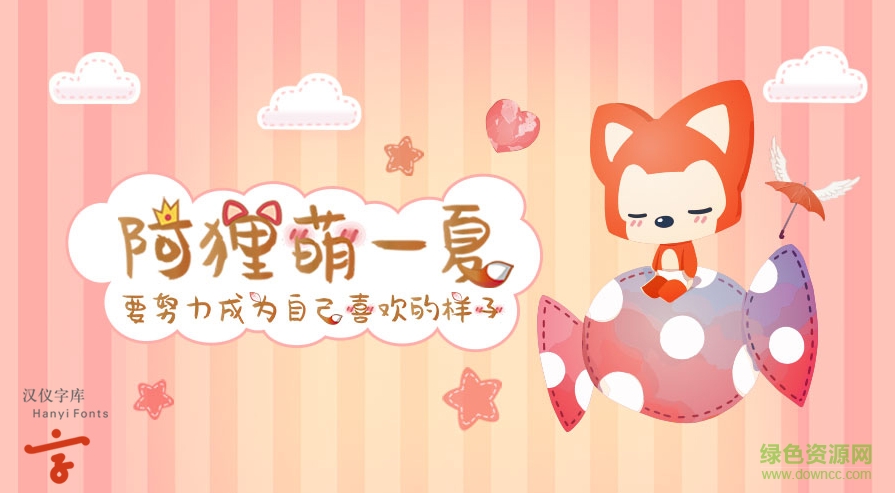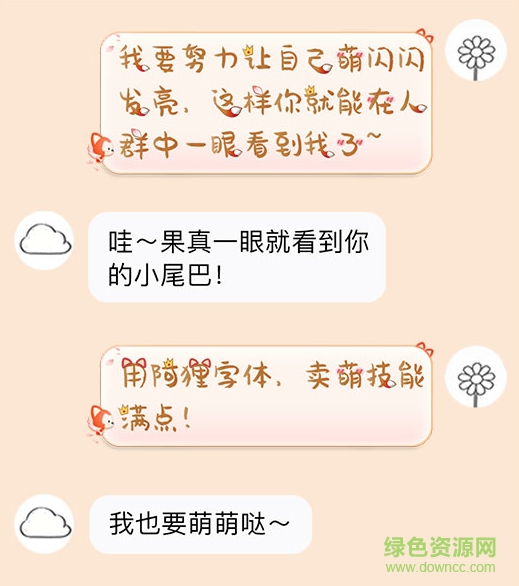
漢儀阿貍萌一夏字體
阿貍萌一夏字體是漢儀字庫(kù)全新推出的動(dòng)漫卡通字體,可愛(ài)的各種萌萌點(diǎn)綴讓你的字體有著生動(dòng)活潑的樂(lè)趣體驗(yàn),如同阿貍在字里行間跳動(dòng),讓你擁有更好的聊天閱讀體驗(yàn),綠色資源網(wǎng)歡迎大家搶先體驗(yàn)!
漢儀字體阿貍萌一夏介紹
“阿貍萌一夏”字體設(shè)計(jì)構(gòu)思?xì)v時(shí)一年,由阿貍作者Hans親自參與,以軟萌可愛(ài)的筆觸,將阿貍首款字體呈現(xiàn)給大家。為了更好的詮釋阿貍和字體的完美結(jié)合,設(shè)計(jì)團(tuán)隊(duì)分別從4本阿貍繪本,以及近千張圖庫(kù)中,尋找能體現(xiàn)阿貍特色的元素。
阿貍萌一夏字體含義
《阿貍·夢(mèng)之城堡》中白色花開(kāi)夢(mèng)里花落的片片花瓣……《阿貍·永遠(yuǎn)站》中站在人海中的阿貍……《阿貍·尾巴》中代表勇氣與愛(ài)的尾巴……《阿貍·旋木花園》中偶遇童話(huà)的小王子……
所有繪本中感人治愈的點(diǎn)滴,都已通過(guò)彩色字體的形式,走進(jìn)尋常的對(duì)話(huà)中,讓童話(huà)變成了一種日常,聊天不再單調(diào),快來(lái)下載使用吧!